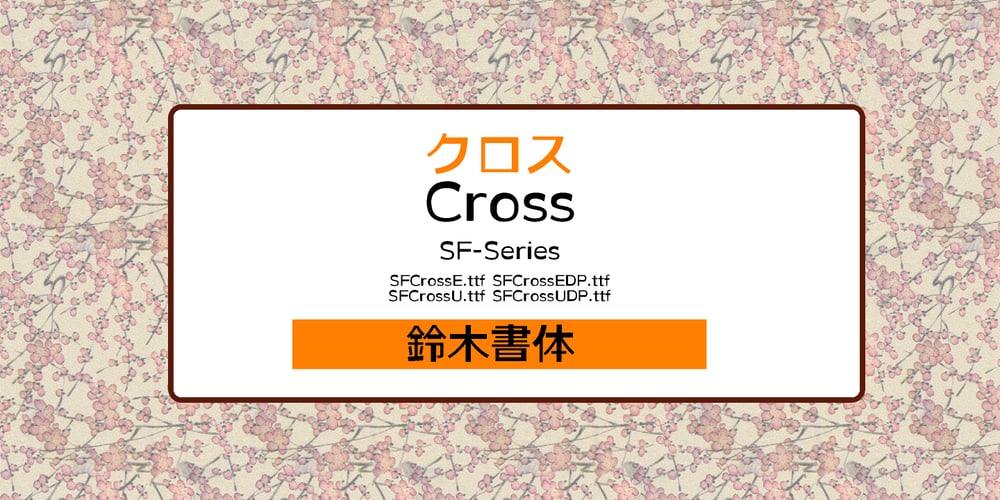
SF Cross
SF Cross font
SF Cross Font Family was designed by published by Fonts66. SF Cross contains 4 styles and family package options. Expressive style for logos and eye catches, titles. 表現力の強い書体。ロゴやアイキャッチ、タイトルに最適。 縦画と横画の太さがほぼ同じのゴシック体の基本を崩して、太さをアトランダムに組み合わせデザインしたのがクロスです。 おやっと思わせるスタイルがアッピール度を高めてアイキャッチを生かしたロゴタイプやヘッドラインなどに適しています。 DPは仮名を大きくし多セットでより強い印象になります。